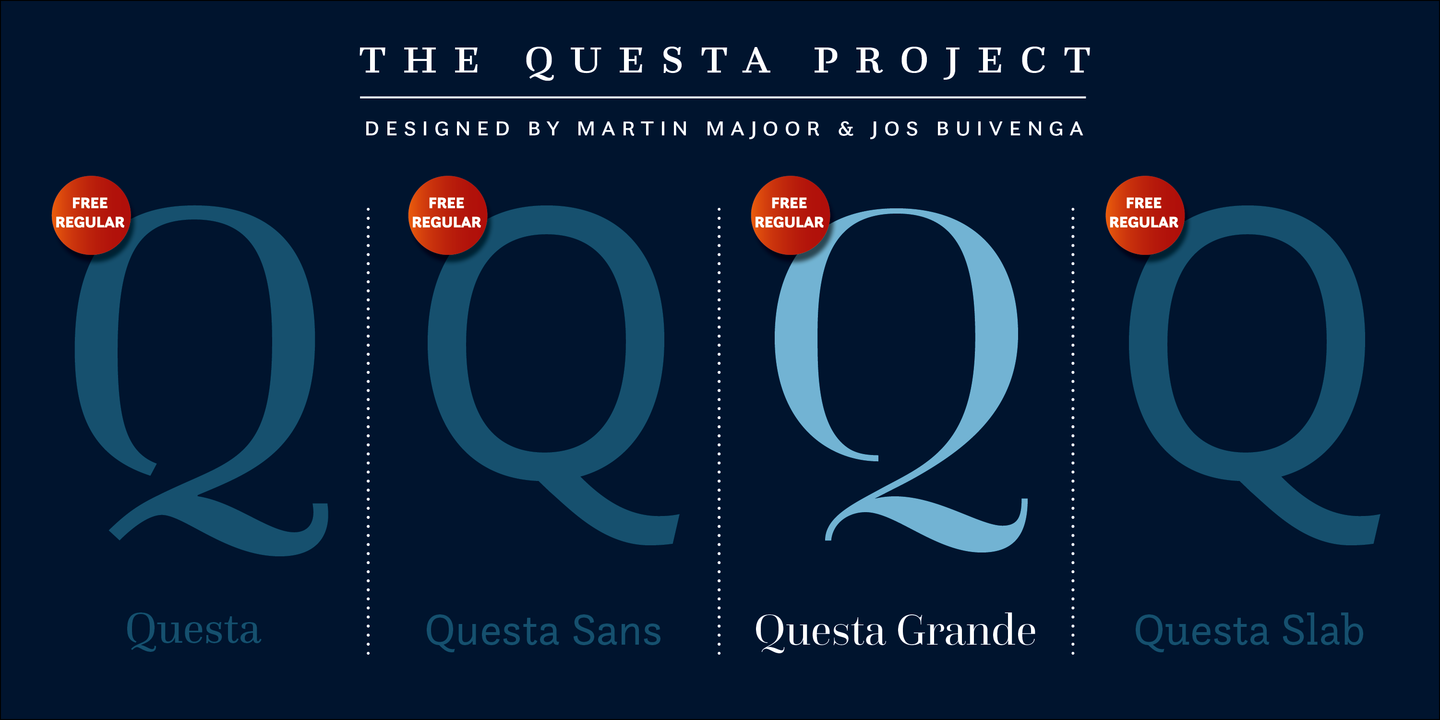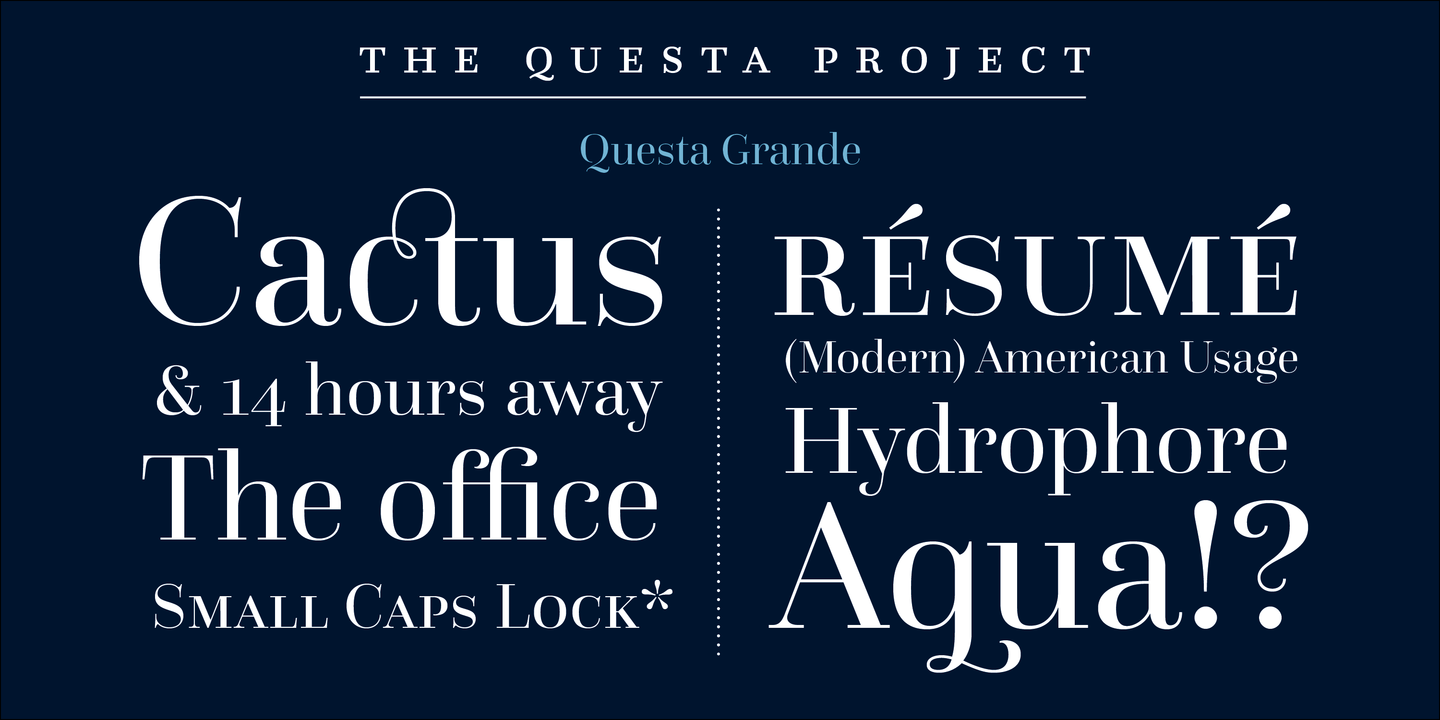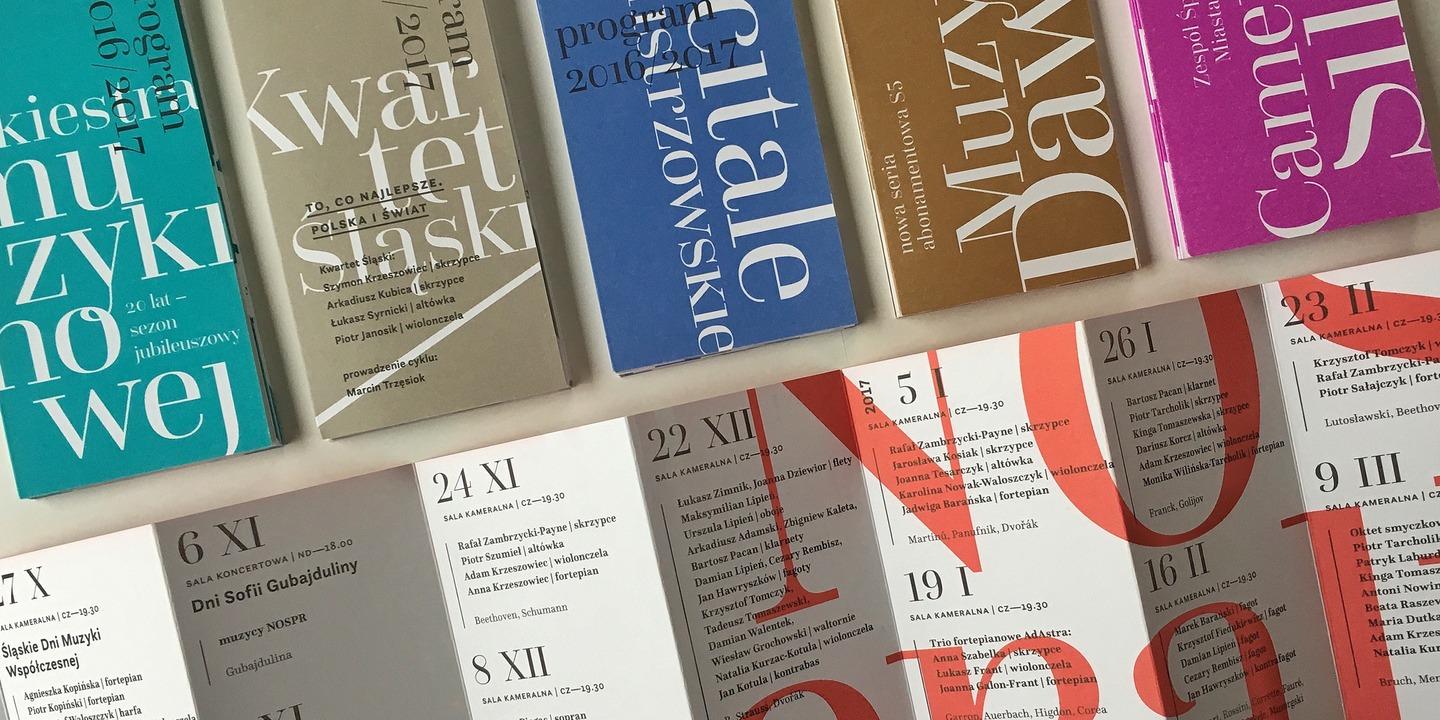
Font-Wiki: Questa Grande
Die Questa Grande von Jos Buivenga und Martin Majoor ist Teil der kommerziellen Questa-Sippe, kann jedoch kostenlos von Fontspring heruntergeladen werden. Die Schrift ist mit ihrem hohen Strichstärkenkontrast speziell auf den Einsatz in Schauanwendungen ausgelegt.
Die Schrift besitzt eine lateinische Belegung mit Kapitälchen und Ziffern in Versal- und Minuskelform (jeweils tabellarisch und proportional).